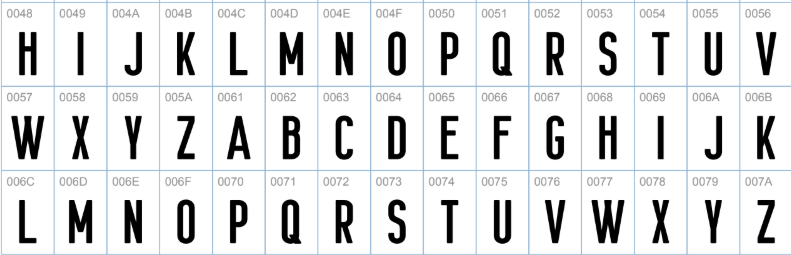
A Liga Deportiva Universitaria, carinhosamente conhecida como “La U” ou LDU, é um gigante do futebol sul-americano e sempre apresenta uniformes que se destacam pela elegância do seu tradicional branco. Para a temporada 2026/27, a parceria com a Puma trouxe uma evolução na identidade visual do clube equatoriano, mantendo a classe habitual, mas incorporando elementos modernos que refletem a nova era do design esportivo.
A tipografia é um dos pontos altos deste kit. Fundamental para designers, colecionadores e editores de games, a fonte utilizada nos uniformes da LDU carrega um DNA tecnológico, garantindo leitura rápida tanto nas transmissões em 4K quanto dentro de campo, na altitude de Quito. Este arquivo é essencial para quem busca recriar com perfeição os mantos do “Rey de Copas” do Equador.
Estilo visual da tipografia
A fonte desenvolvida para a temporada 2026/27 da LDU segue as diretrizes globais da Puma, mas com personalizações exclusivas para o clube.
• Estética: Trata-se de uma fonte moderna, com linhas limpas e cortes geométricos sutis que evitam o excesso de curvas. O visual é “blocky” (blocado), transmitindo solidez e força, características históricas da defesa da Liga.
• Aplicação: No uniforme titular (Home), totalmente branco, a fonte é aplicada geralmente em azul escuro ou preto, garantindo contraste máximo. Nos uniformes alternativos (Away e Third), a tipografia pode aparecer em branco ou tons de cinza, dependendo da base da camisa.
• Personalidade: A fonte foge do retrô e abraça o futurismo minimalista. Os números possuem uma espessura média-alta, ideal para visibilidade à distância, e os nomes dos jogadores seguem um kerning (espaçamento) equilibrado, típico dos padrões internacionais da Puma.